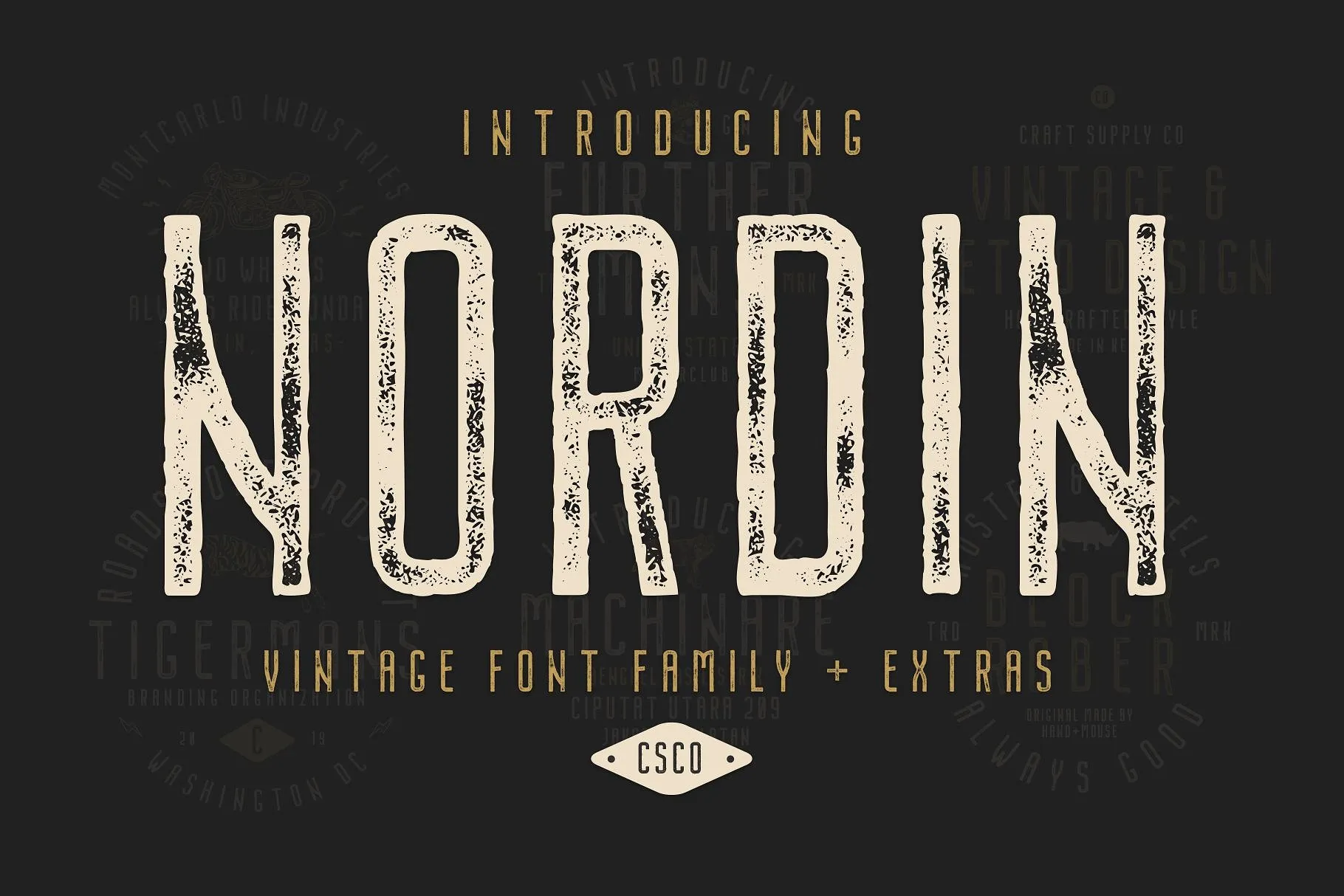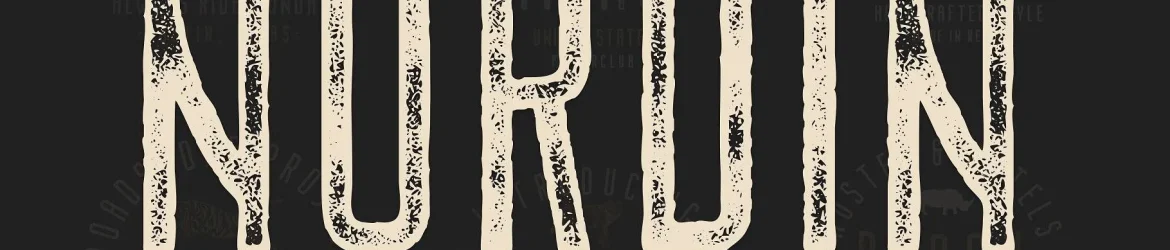
Nordin Vintage Font Family – Download Grátis
A Nordin Vintage Font Family é uma nova família de tipo vintage sans serif lançada pelo designer 24Design. Esta famosa família de tipos inclui quatro estilos, adequados para criar diversos projetos gráficos impressos. Não há limitação para o tipo de projeto que você pode desenvolver com ela — basta usar sua imaginação e adicionar uma paleta de elementos extras, e seu trabalho estará mais vivo e atraente do que nunca. A Nordin Vintage é perfeita para os projetos em papel ou digital, seja em cartazes de eventos, folhetos de marketing, capa de revistas ou qualquer outro tipo de design visual. Seja criativo com essa fonte vintage, ela certamente ajudará a destacar seus trabalhos de design e torná-los ainda mais memoráveis.